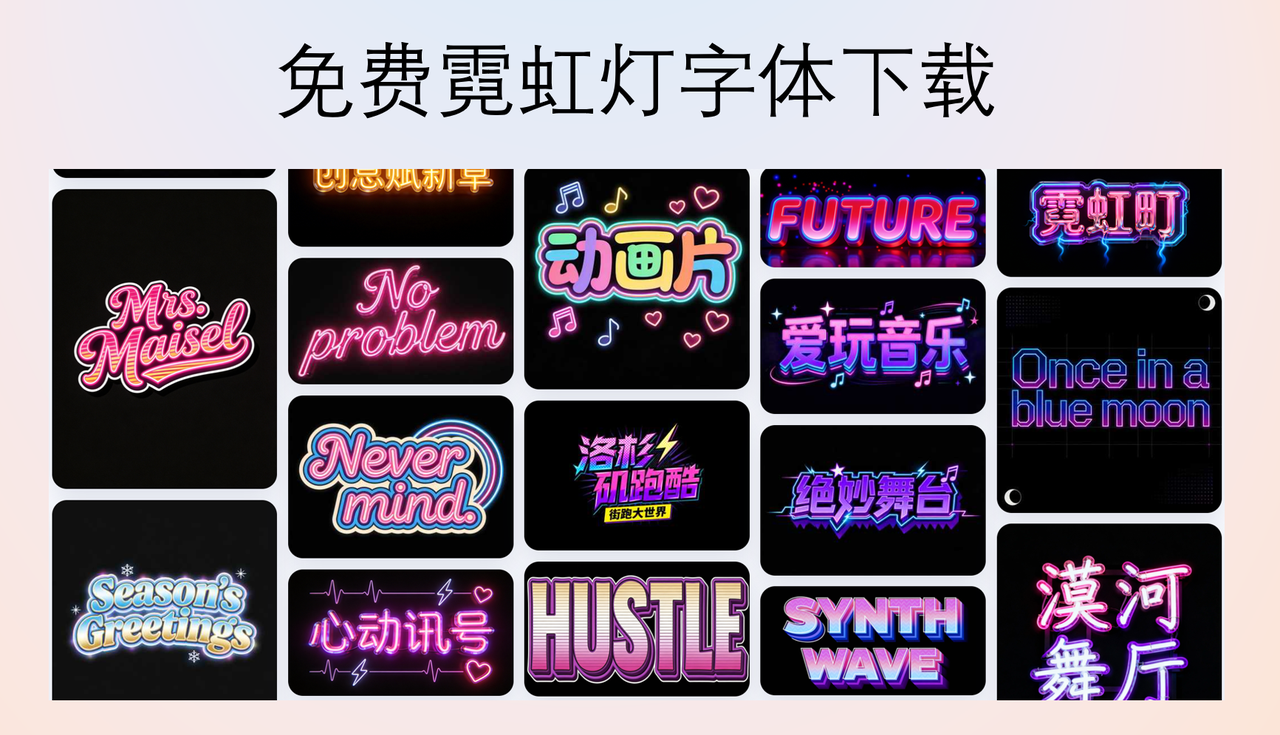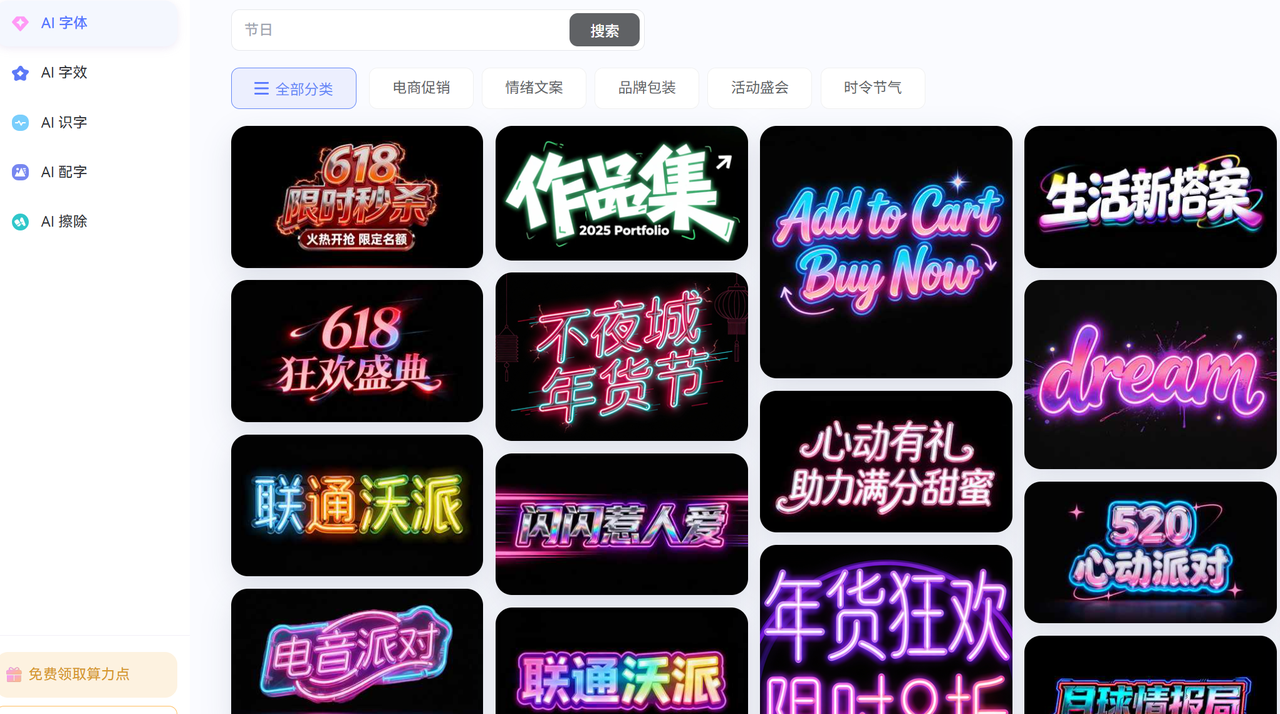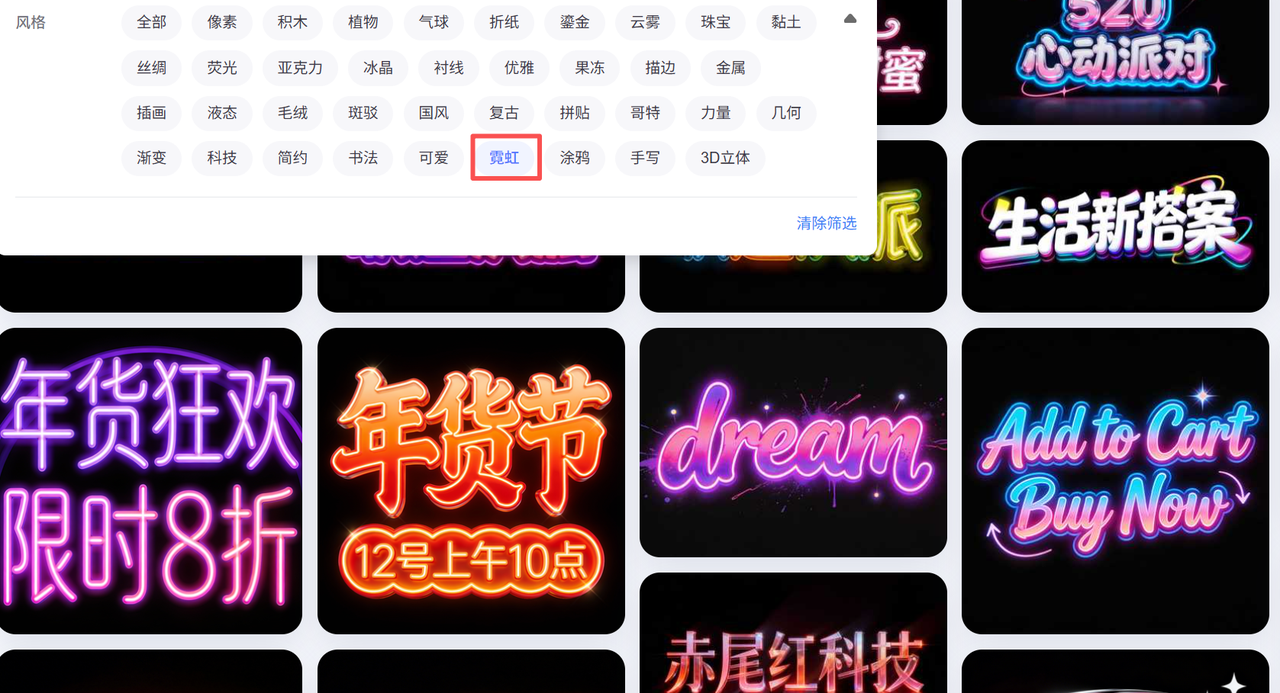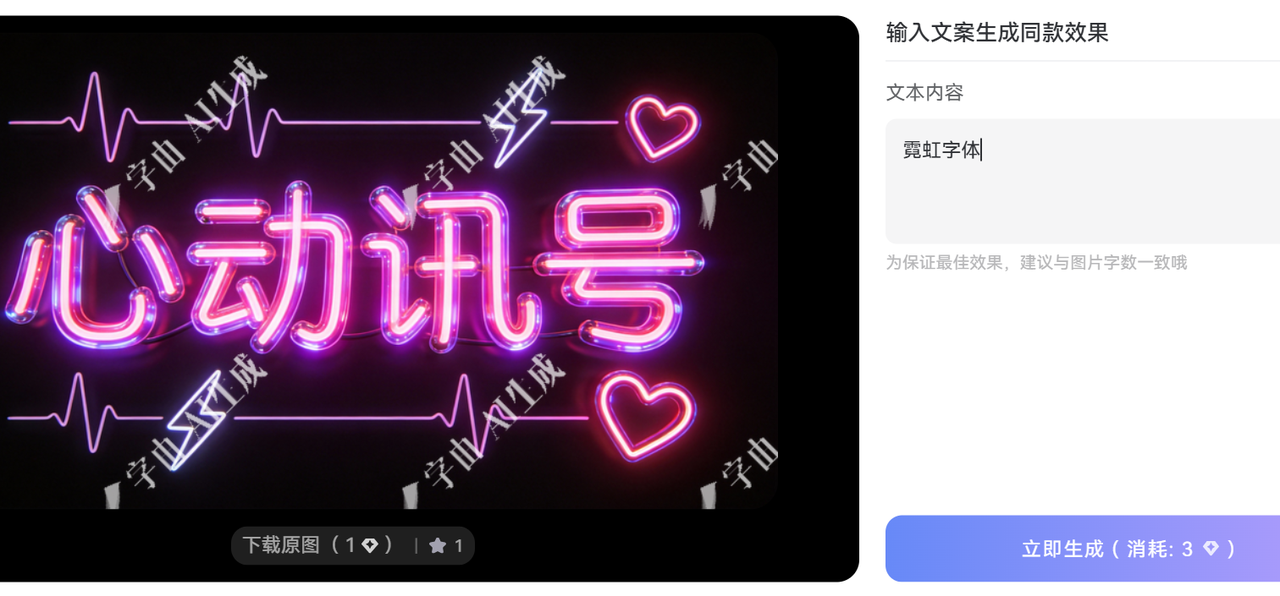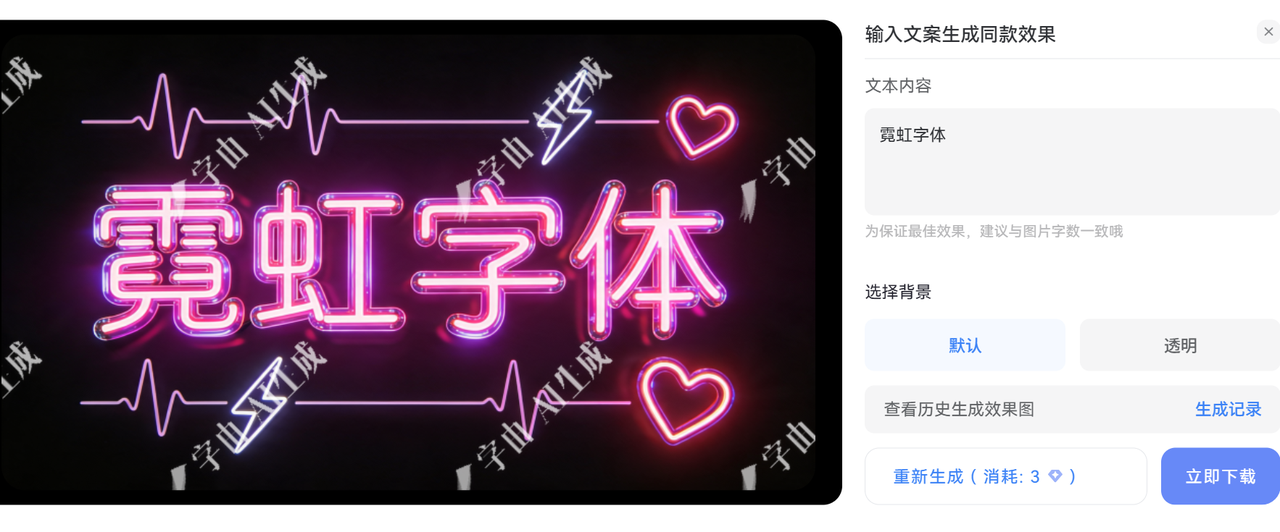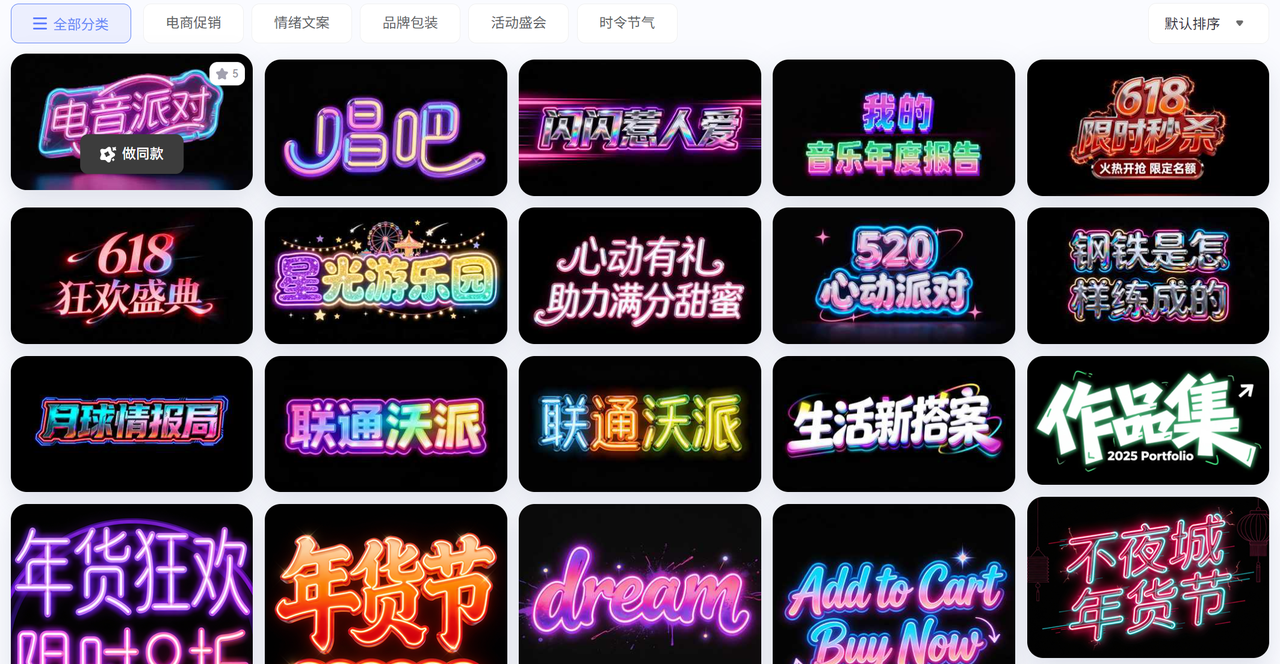
免费商用的霓虹灯字体下载指南:利用 AI 快速生成高质感艺术字
你在设计海报或者制作短视频封面时,想要那种电流涌动、赛博朋克感十足的视觉效果,却发现市面上大多数好看的霓虹字体,并不是那么好找,今天,我想和你分享一个非常实用且零成本的解决方案,让你告别侵权烦恼,轻松下载可商用的霓虹灯艺术字。
AI 生成霓虹灯字体介绍
在过去,想要做出一款逼真的霓虹灯字,往往需要依赖设计师在 Photoshop 里花费几小时去调整光晕、阴影、外发光等复杂的图层样式。如果遇到复杂的排版,调整起来更是没完没了。
最近,我发现了“字由AI字体”这个工具。它最吸引我的地方在于,你不需要是一个资深平面设计师,甚至你不需要有设计基础,也能快速生成霓虹灯艺术字体。只需要描述你想要的风格,比如“霓虹、可爱”,系统就能快速帮你筛选出匹配的字体模板。选择喜欢的模板,输入自己的文字,即可一键生成同款。整个过程几分钟就能完成。
免费商用的霓虹灯字体下载教程
操作过程其实非常简单,你只需按照以下步骤进行:
2. 在字体风格中选择“霓虹”,或者在搜索框中直接进行搜索,比如“霓虹灯”、“发光”等等
1. 根据自己的需求和喜好,选择霓虹字体模板,可以多选择几个,方便做对比
2. 输入自己的文字,点击一键生成
1. 下载与使用:选择满意的效果后,直接下载即可在后续的图片处理或视频剪辑软件中使用。
AI 生成霓虹字体的独特优势
操作简单,方便快捷
不用在 PS 中进行复杂长时间的操作,只需要筛选、输入、点击即可完成字体生成,下载也比较方便。
视觉表现更强
很多传统的霓虹字体只是改变了字形,而 AI 生成的图片直接包含了“发光”这一物理特性。它能模拟真实霓虹灯在空气中的光晕弥散效果,让设计稿看起来更真实,更有质感。
使用这些工具,并不是为了完全取代设计工作,而是为了把我们从重复性的机械劳动中解放出来。当我们不需要再为素材版权揪心时,就能把更多的精力放在作品本身的创意表达上。